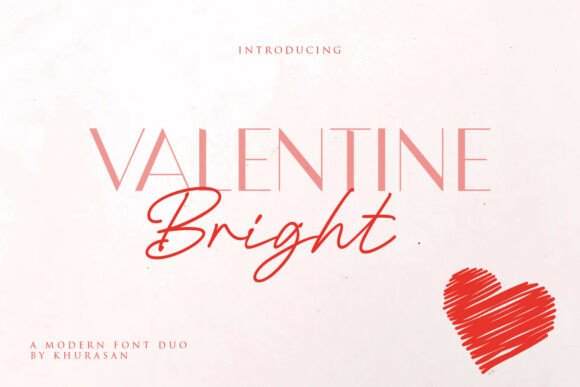
Valentine Bright Duo
Mencari elemen reka bentuk yang sesuai boleh menjadi mencabar, tetapi Valentine Bright Duo menawarkan koleksi luar biasa yang menaik taraf karya anda serta-merta.
Sama ada anda mencipta produk POD (Print on Demand), jemputan perkahwinan atau grafik media sosial, Valentine Bright Duo amat bersesuaian.